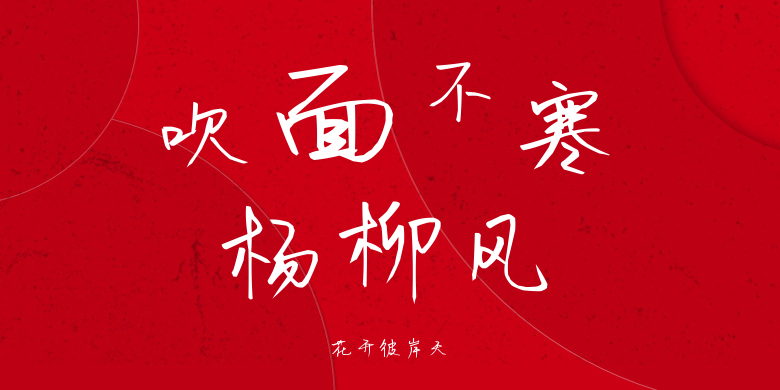
花开彼岸天
花开彼岸天,这款字体结构工整、笔画清晰,兼顾美观与易读性,适用于标题、正文、海报、包装、LOGO 等多种场景。字形优雅稳定,风格百搭耐看,适配日常排版与创意设计,让文字呈现更舒适、更具质感。花开彼岸天一笔一画,皆是细节,以均衡的比例、流畅的线条打造舒适视觉体验,字形端正大气,风格简约现代。无论是商业设计、品牌宣传还是日常排版,都能轻松驾驭,让文字更有格调与力量。花开彼岸天字体下载。